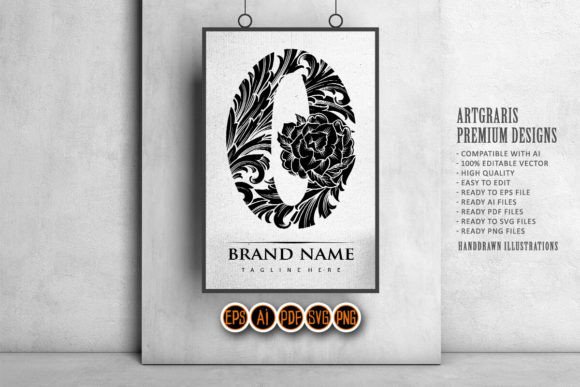
Classic Design Elements Distinctive
Classic Design Elements Distinctive – Review Completa
Se você está em busca de uma ilustração vetorial que una elegância clássica e versatilidade para seus projetos, o Classic Design Elements Distinctive é a escolha ideal. Este pacote de arquivos oferece a tipografia “capital O” em estilo clássico, perfeito para quem deseja dar um toque sofisticado a camisetas, tote bags, adesivos, banners, cartões comemorativos, flyers, pôsteres e muito mais.
Por que este design se destaca?
Aplicações práticas
Com este recurso, você pode criar:
- Estampas exclusivas para t‑shirts e hoodies
- Designs atraentes para tote bags e sacolas ecológicas
- Adesivos e stickers com acabamento profissional
- Cartões de felicitação, convites e postcards personalizados
- Materiais promocionais como flyers, banners e pôsteres de alta qualidade